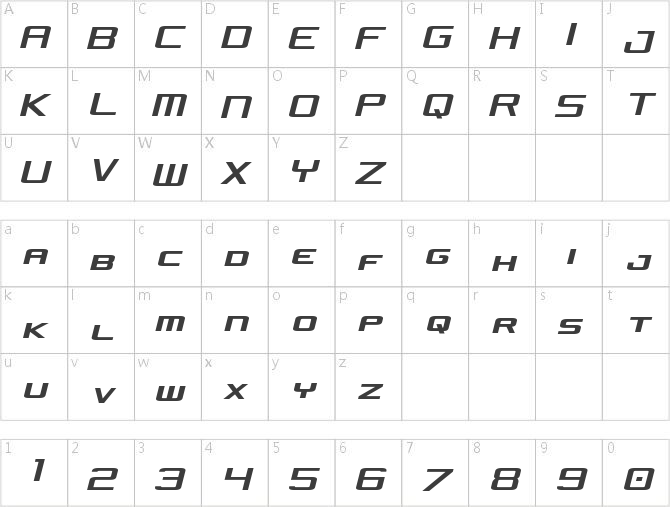
Concielian Jet Condensed Semi-I
Concielian Jet Condensed Semi-I介绍
Concielian Jet Condensed Semi-I字体字库是一款让人赏心悦目、百看不厌的英文字体,适合各类广告和产品包装设计应用,字体大小0.03MB,格式为ttf字体,上传用户是/zyj【GF】,作者/版权方为未知